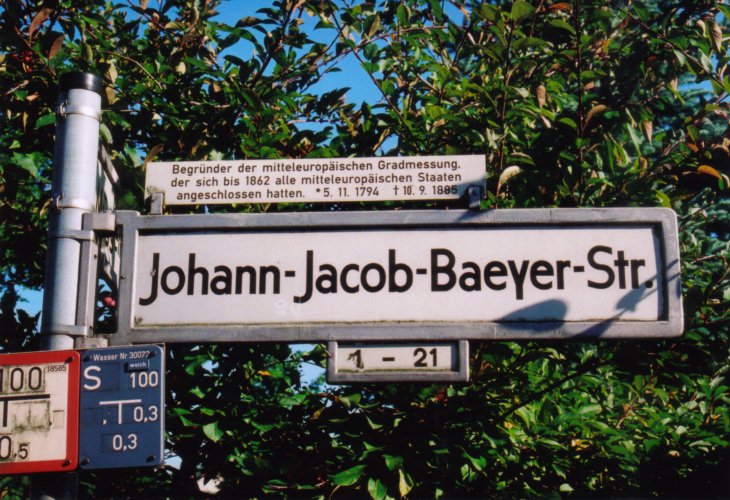
Schrift für tz-Ligatur
Kann mir jemand eine Schrift mit einer schönen tz-Ligatur empfehlen? Keine Fraktur. Danke!
Hey, klasse. YanoneKaffeesatz ist genau das, was ich wollte... danke!
In diesem Zusammenhang vielleicht auch noch ganz interessant, obwohl Du bereits gefunden hast, was Du suchst.
Berliner Straßenschilder (Schrift in Anlehnung an Herbert Thannhaeuser)
Es gibt eine Schrift: FF Cst Berlin, die diesen Berliner Straßenschildern nachempfunden ist. Ob die allerdings auch die Ligatur tz enthält, habe ich jetzt aber noch nicht nachgeprüft.
Bonner Straßenschildern (mit Ausnahme der ganz alten und neuen) sehen den Berlinern zum Verwechseln ähnlich (besonders gut zu sehem am markanten »ß« dieser Schriftart). Allerdings wird in Bonn nicht die tz-Ligatur verwendet.
Im Osten von Berlin begegnet man der CST Berlin nur auf neuen Straßenschildern. Ältere (imho noch aus DDR Zeiten) verwenden eine andere Schriftart.
Das rechte Schild ist typisch für den Osten von Berlin. Das linke Schild ist untypisch und sah ziemlich neu aus.
hier ist das Eszett der Berliner Straßenschilder
Ich grabe diesen alten Beitrag mal wieder aus...
Suche eine serifenlose Schrift für Fließtext mit eben so einer schönen tz-Ligatur, wie sie in CST Berlin West oder Yanone Kaffeesatz vorhanden ist.
Yanone Kaffeesatz ist mir zu schmal, Fließtexte sind schlecht lesbar. CST Berlin West ist schön, aber da ich in Berlin wohne möchte ich gerne eine Alternative, so in die Richtung der Hausschrift des Flughafens Berlin-Brandenburg.
CST Berlin West
Weiß jemand, was es mit dem unkonventionellen y auf sich hat, das eher wie ein ү (Cyrillic straight u) aussieht? Ist das wirklich so verwendet worden?
Spannend, ist mir bei meinen gar nicht so seltenen Westberlinbesuchen nie aufgefallen. Gibt es dafür historische Vorbilder oder ist das eine West-Berliner Schildereigenart?
Weiß denn jemand eine Schrift (mit o.g. Kriterien), in der ein geschwänztes Z vorhanden ist?